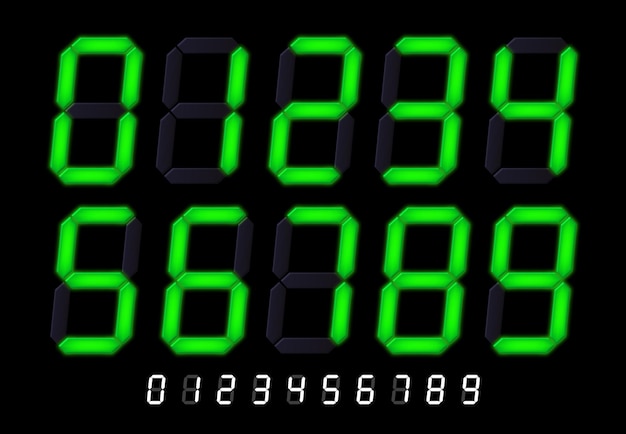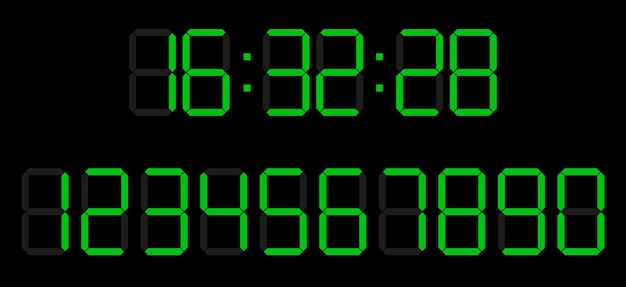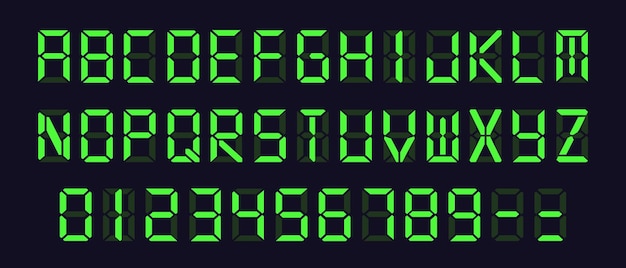
Сегментированные числа ЖК-дисплея Цифровой таймер знаки технический счетчик часов или ретро-светодиодный экран калькулятора шрифт векторный набор векторный набор